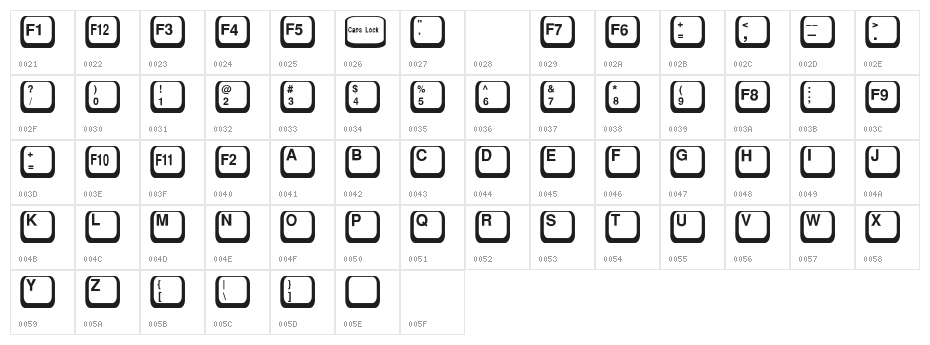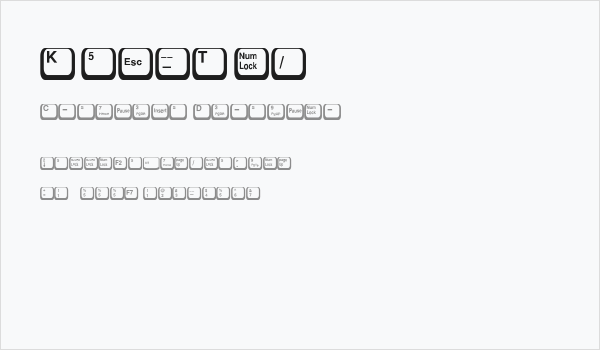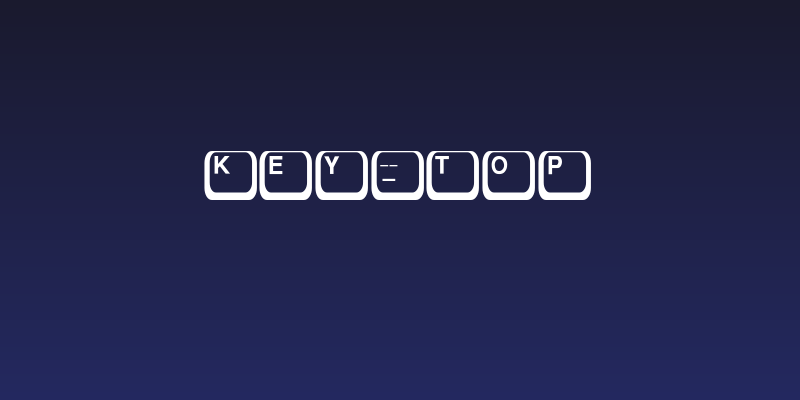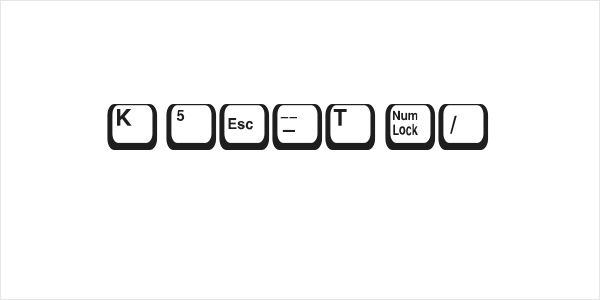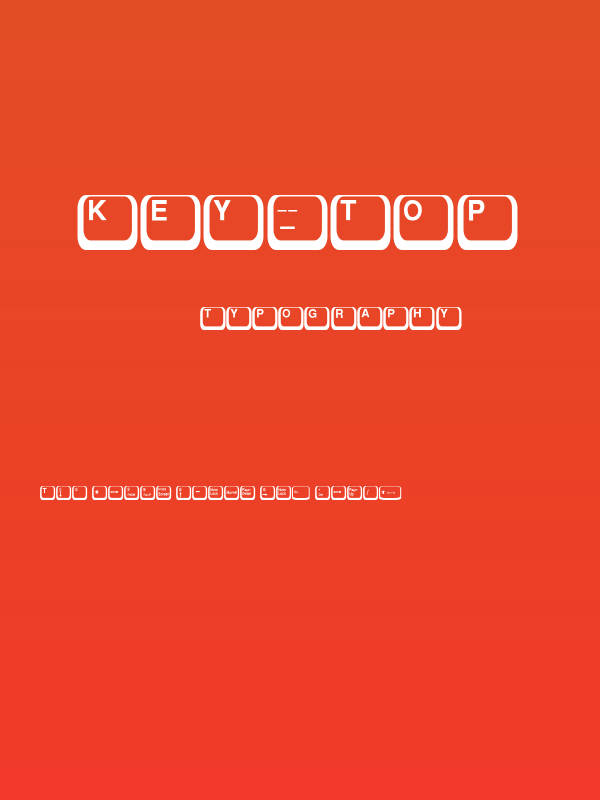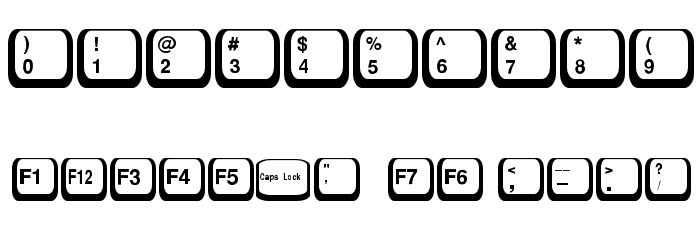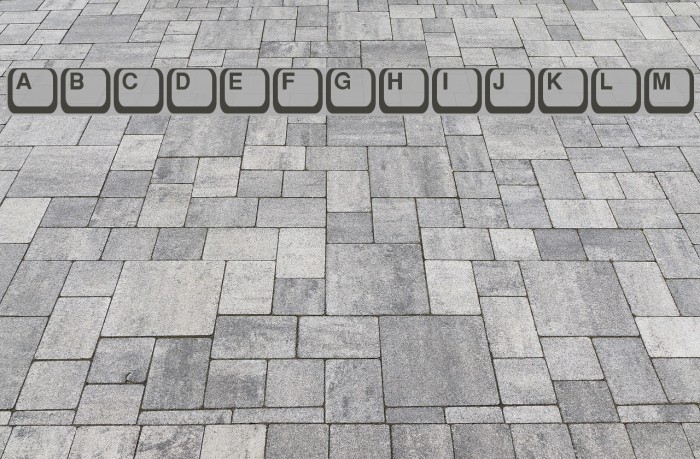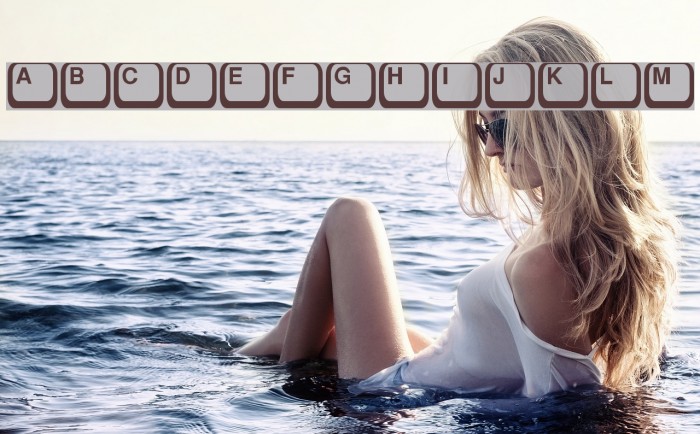
Key-Top Font
| Caso de uso | Logos, Headlines, Posters |
| Proyectos propuestos | Ideal for tech-themed designs, educational materials, or any project requiring a modern, digital aesthetic. |